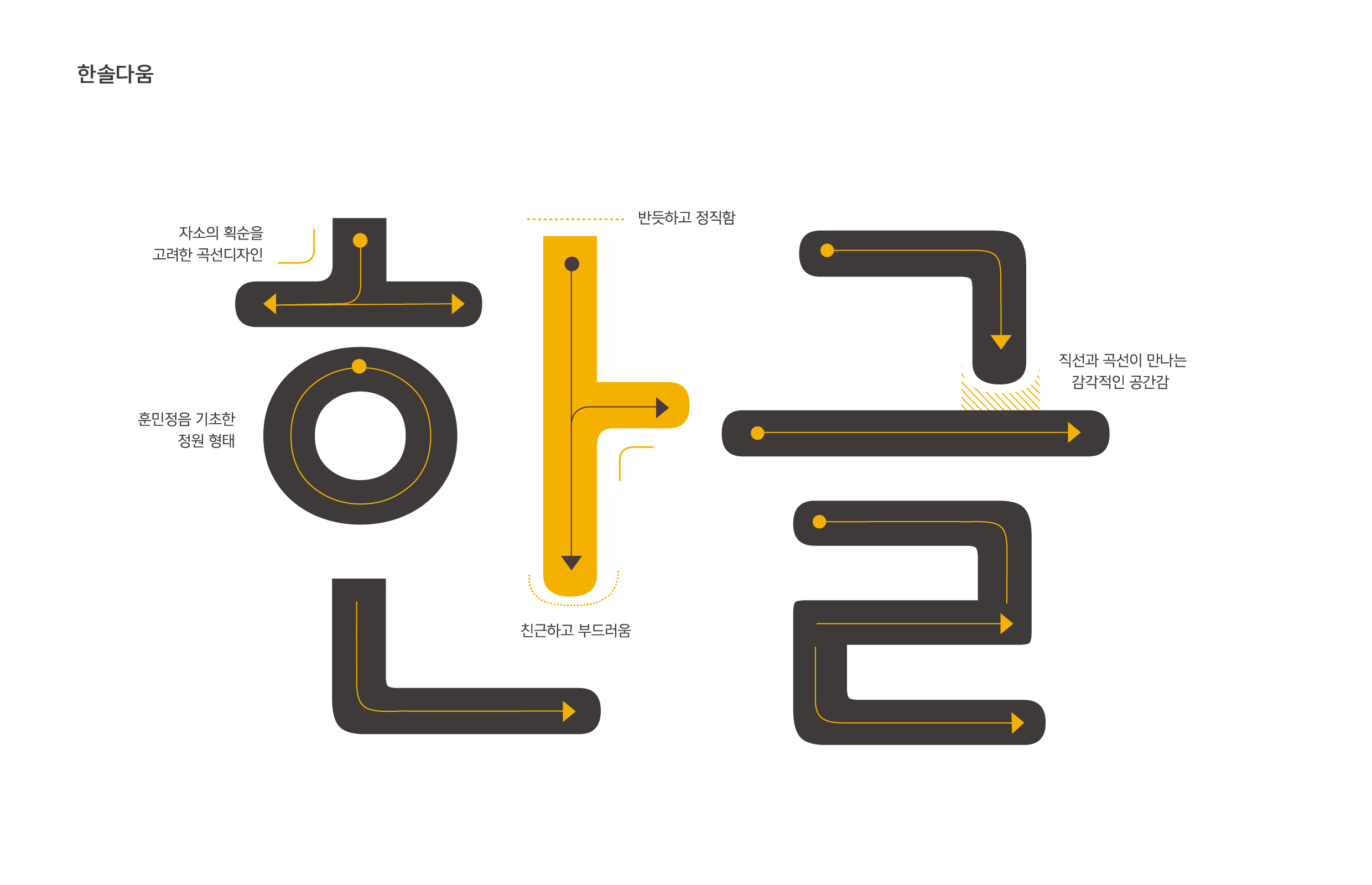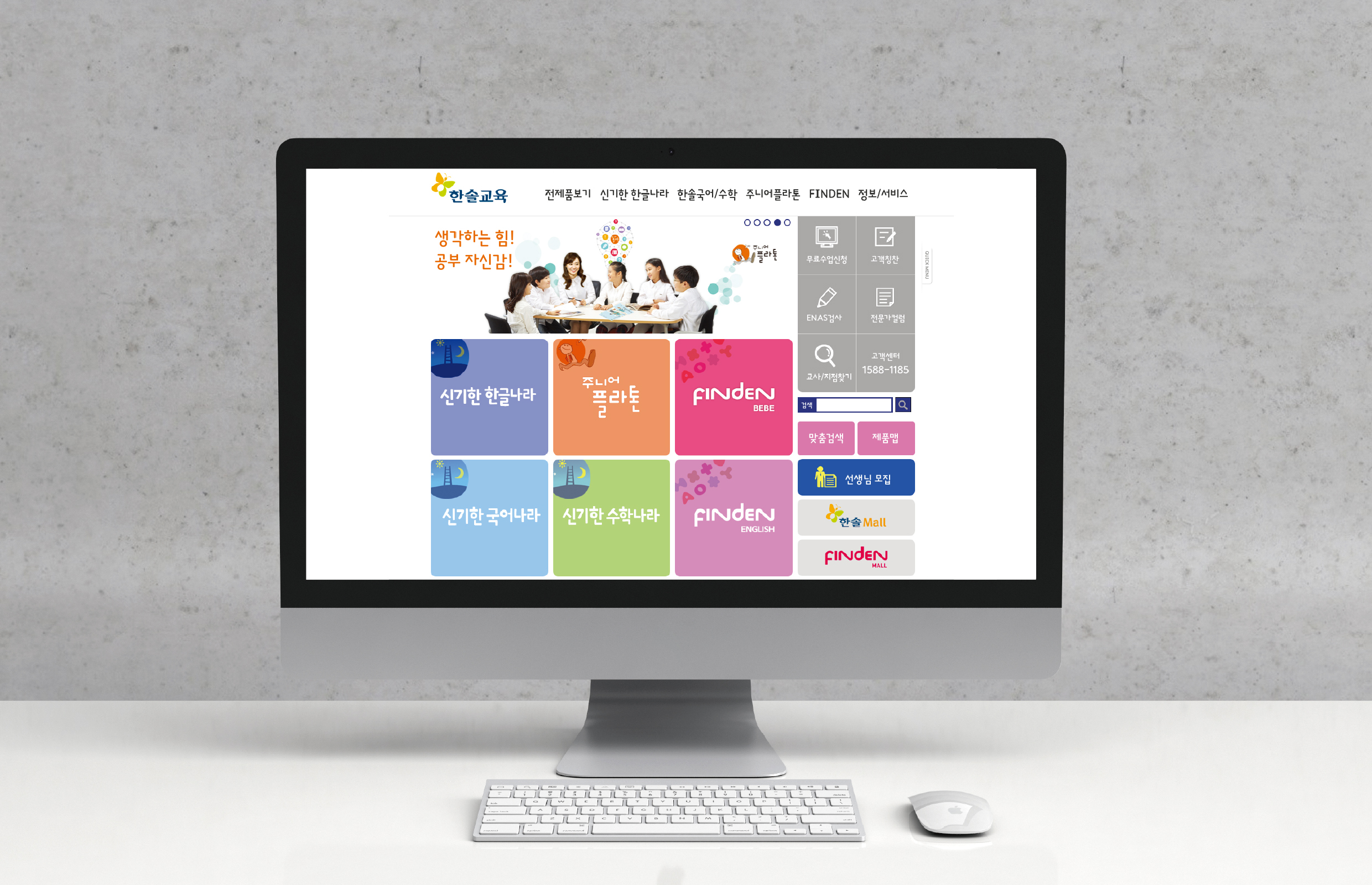
한솔교육
한솔교육 [한솔다움, 한솔아름]
한솔교육의 정신을 바탕으로 아이들의 원시적 필기법과 자소의 기본 획 순서를 고려하여 디자인한 서체. 훈민정음 해례본에 입각한 기본 자형을 토대로 자모음의 형태가 설계되었으며, 바르고 정직하게 한글교육에 앞장서는 한솔교육의 이미지를 담아냈다.